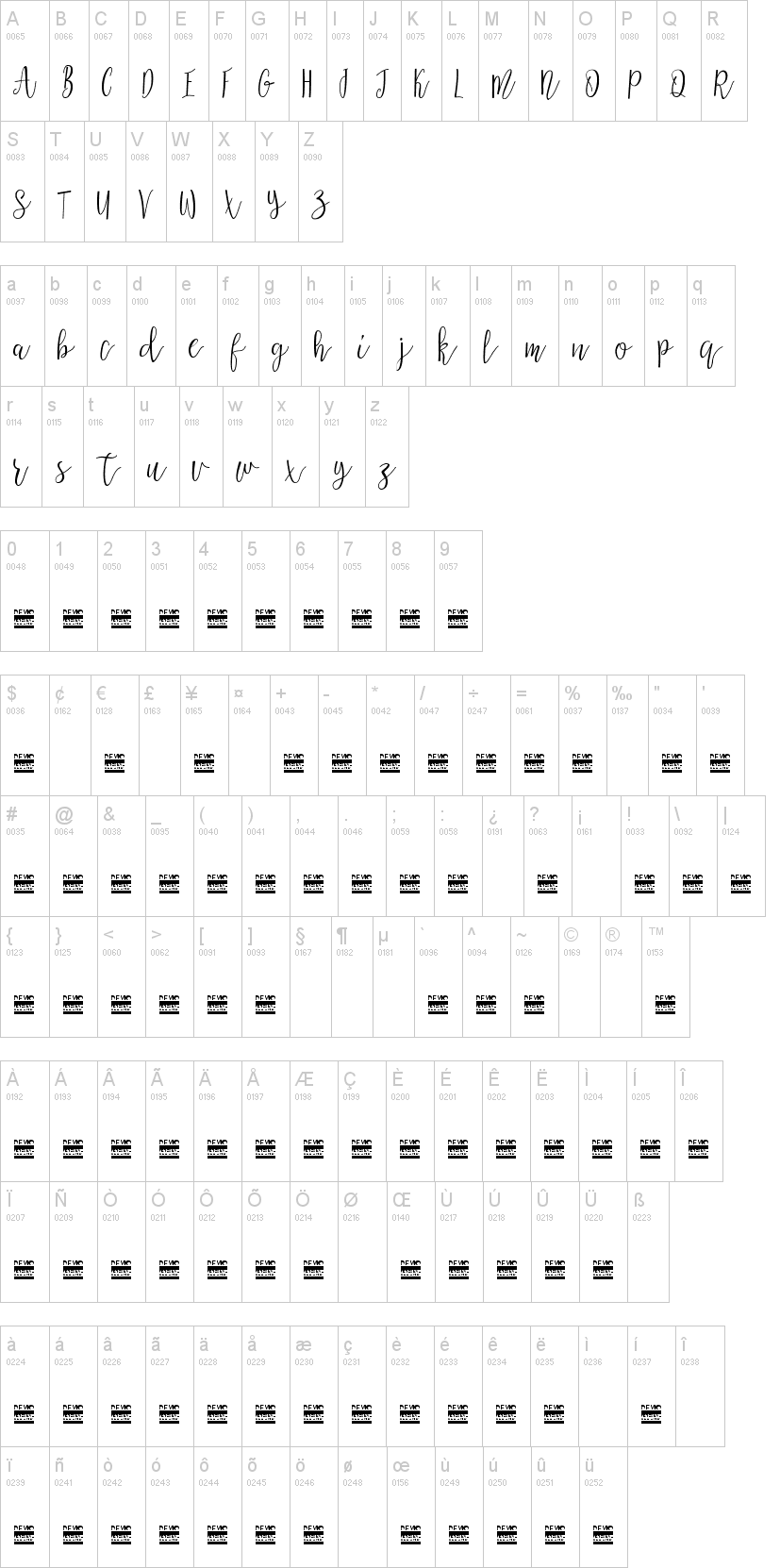
Aziya字体是一款来自俄罗斯的手写体字体。它是由一位设计师在2013年创作的,它具有温柔而优雅的特点,能够给文字带来温暖和浪漫的气息,适合用于报纸、杂志、小说、海报等等。它的字体更加柔软,更有活力,而且拥有许多细节,可以让文字更加有趣和生动。内容介绍
Aziya是一款非常不错的手写艺术字体,具有很好的视觉感,适合于文化类的宣传设计、商业类品牌的广告和产品包装设计以及个性化文字排版等较多场景。